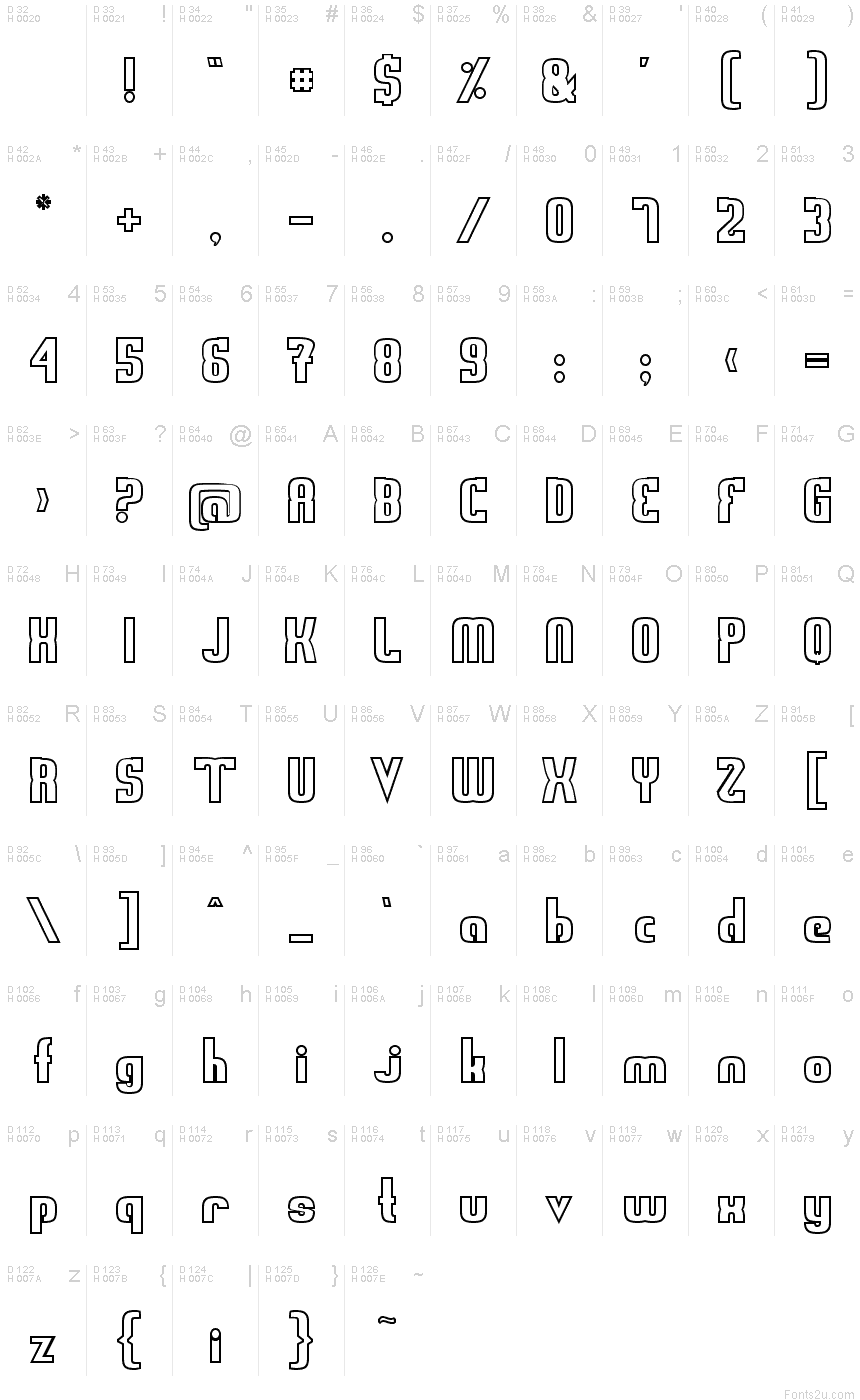
Sweden Funkis Outlined
Sweden Funkis Outlined, autorstwa Samuela Parka, to darmowy, konturowy krój pisma typu display, utrzymany w duchu miękkiego modernizmu i liternictwa lat 70. Znaki zbudowano z szerokich, zaokrąglonych kształtów o wyraźnych obrysach, dzięki czemu całość sprawia wrażenie lekkiej i zabawnej, a nie ciężkiej – przywodząc na myśl schludny, skandynawski styl plakatowy.
Sprawdzi się wszędzie tam, gdzie nagłówek potrzebuje osobowości bez przytłaczania solidnym kolorem: w identyfikacji kawiarni, na okładkach magazynów, ulotkach muzycznych, opakowaniach czy krótkich hasłach na plakatach. Jako darmowy font jest szczególnie przydatny przy projektowaniu tytułów i szkicowaniu logo – otwarty kontur dodaje tekstowi lekkości, a wyraziste, krągłe kształty świetnie wypełniają przestrzeń.